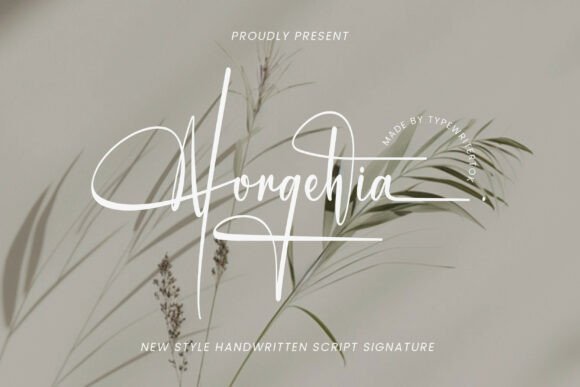
Norgehia
Ulasan Lengkap Norhegia: Font Signature yang Memukau untuk Semua Kebutuhan Desain
Jika Anda sedang mencari font signature yang menonjolkan elegansi dan keanggunan, Norhegia adalah pilihan terbaik. Dengan goresan yang mengalir dan nuansa tulisan tangan alami, font ini menghadirkan sentuhan personal yang sempurna untuk berbagai aplikasi, mulai dari branding dan logo hingga undangan pernikahan dan kemasan mewah.
Berikut ini ulasan lengkap tentang apa yang membuat Norhegia begitu istimewa, serta panduan praktis untuk memanfaatkannya dalam proyek desain Anda.
Karakteristik Utama Norhegia
- Goresan Alami – Setiap huruf terasa seperti tulisan tangan asli, memberikan kesan lembut namun kuat.
- Elegan dan Sophisticated – Desain ini didesain khusus untuk menonjolkan kesan mewah dan profesional.
- Fleksibel – Cocok untuk branding, logo, undangan pernikahan, kartu nama, posting media sosial, dan kemasan produk.
Manfaat Menggunakan Norhegia dalam Desain
- Menambah keunikan pada identitas merek Anda.
- Memberi kesan profesional dan berkelas pada undangan pernikahan.
- Memudahkan pembaca memahami pesan dengan stroke yang jelas.
- Menambah sentuhan personal pada kartu nama dan materi pemasaran.
- Meningkatkan engagement pada posting media sosial berkat visual yang menarik.
Kesimpulan
Norhegia bukan sekadar font; ia adalah simbol keanggunan yang dapat memperkuat identitas merek dan memberikan sentuhan personal pada setiap proyek desain. Dengan kombinasi goresan alami, fleksibilitas, dan kemampuan SEO yang terintegrasi, font ini siap membantu Anda menciptakan karya yang tak terlupakan.